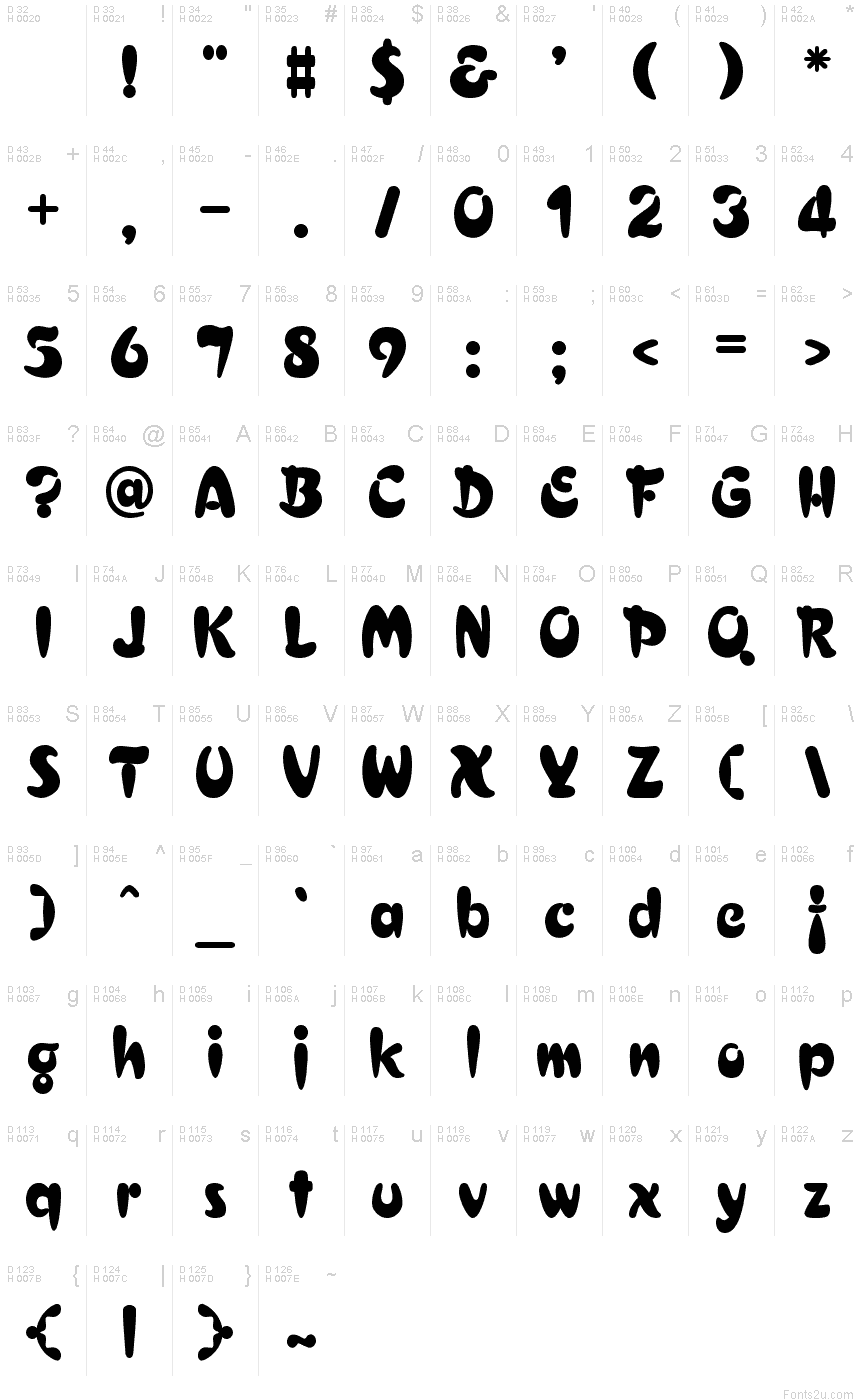
Electrik di A. Carr è un font display gratuito in stile fumetto, caratterizzato da forme spesse e scure che richiamano il taglio manuale. Le lettere rimbalzano con un ritmo giocoso e irregolare – come un timbro che ha ricevuto una scossa – rendendo anche le parole brevi animate e d'impatto, senza bisogno di effetti aggiuntivi.
Con Electrik, darai subito personalità ad adesivi, inviti per feste, titoli di fumetti, packaging di snack, flyer musicali, copertine YouTube e poster creativi. Usala in grandi dimensioni per mantenere nitide le sue curve morbide e abbinala a un font sans serif pulito per il testo di supporto: questo font gratuito ama stare al centro della scena.